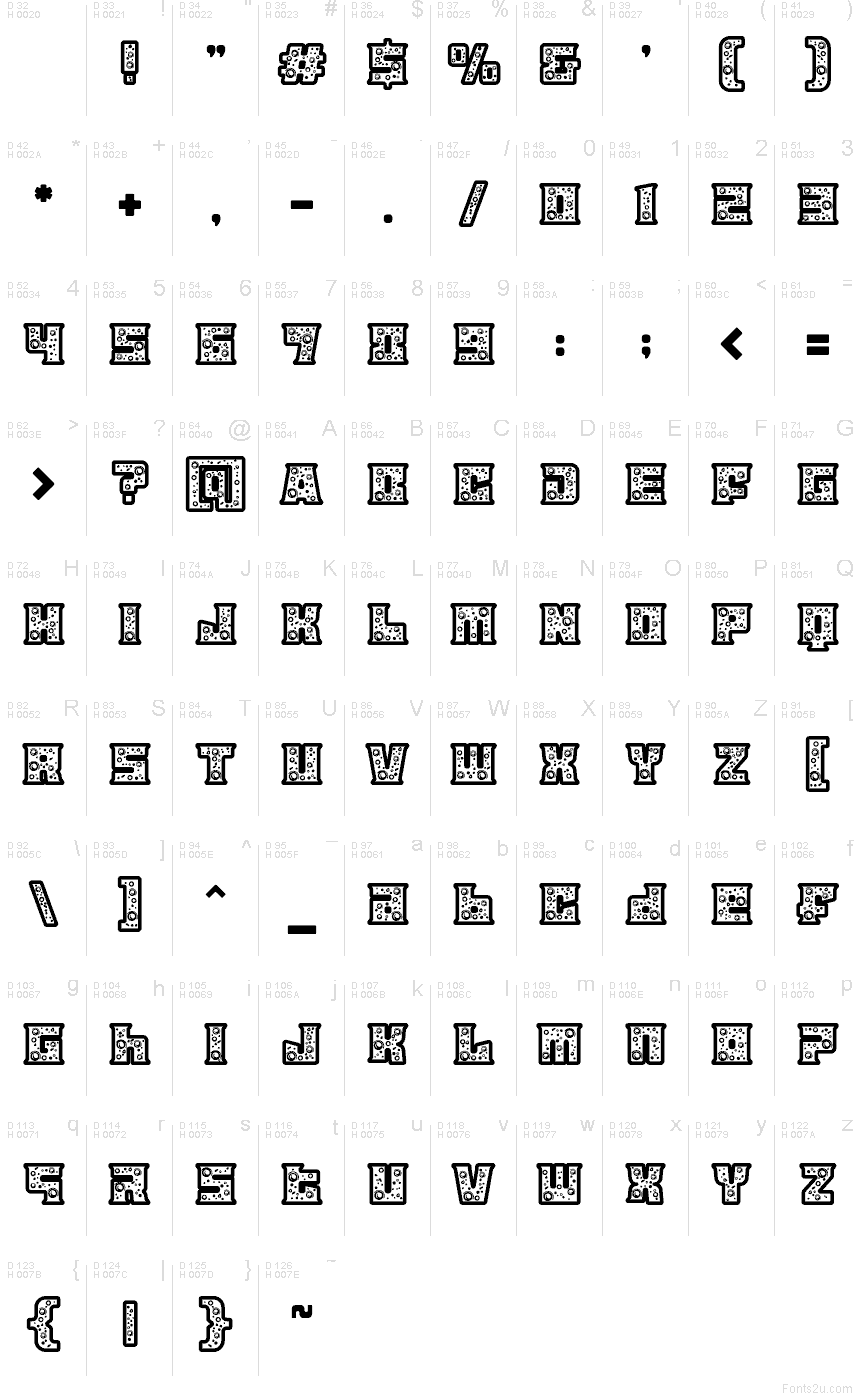
Astral Zenith Ten od Putracetol Studio je bezplatný font s vesmírnou tematikou, jehož zúžené a hranaté znaky jsou plné kroužků, roztroušených teček a zářezů připomínajících krátery. Tento opakující se povrchový vzor způsobuje, že design nepůsobí jako běžná dekorace, ale spíše jako písmo vytažené přímo z animovaného kosmu.
Font má dostatečnou grafickou váhu pro titulky na plakátech, herní obrazovky ve stylu arkád, grafiku pro planetária, letáky vědeckých klubů a originální obaly, kde hvězdná textura sama o sobě vypráví část příběhu. Nejlépe vynikne v krátkých nadpisech a logách, protože bohaté vnitřní detaily dodávají každému slovu výraznou tematickou siluetu bez nutnosti dalších ilustrací.
Astral Zenith Ten